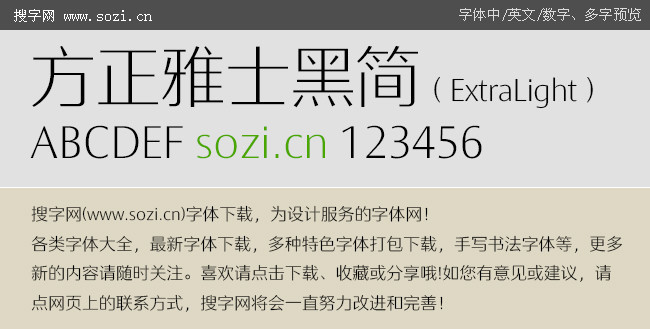
方正雅士黑ExtraLight
搜字網(wǎng)提供一款方正雅士黑ExtraLight中文字體下載。雅士黑系列字體是具有典雅氣質(zhì)的風(fēng)格化黑體作品。創(chuàng)作靈感來(lái)源于經(jīng)典的拉丁文字體Optima,其筆畫(huà)橫縱比例約為1:3,兼具了黑體的簡(jiǎn)潔和宋體的雅致特征。 整體字形方正,剛?cè)嵯酀?jì),優(yōu)雅大方。雅士黑擁有6個(gè)字重,可以涵蓋正文和標(biāo)題的排版使用。 適用范圍:商業(yè)廣告、書(shū)刊出版、產(chǎn)品包裝設(shè)計(jì)。